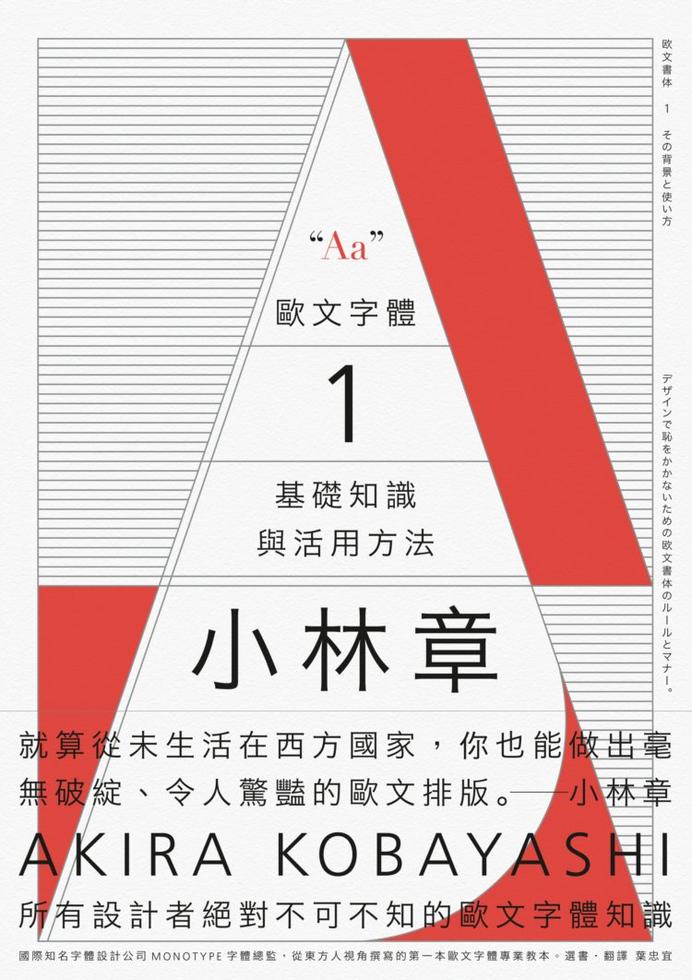
歐文字體(1)──基礎知識與活用方法
小林章
「就算從未生活在西方國家,也能做出毫無破綻、令人驚豔的歐文排版。」
歐文字體基礎知識X經典字體特色與選用方法X排版原則與規範
國際知名字體設計公司Monotype字體總監--小林章
從東方人視角撰寫的第一本西洋字體專業教本
所有設計者不可不知的字體知識
──從歷史起源、用語解說、經典字體解析等觀念知識,到字體設計、辨識、選用、業界規則等實戰技巧,讓你有系統地通盤理解歐文字體,徹底活用!
本書作者小林章,在獲得多項國際字體設計大獎後,受聘至字體大廠德國Linotype(現和Monotype字體公司合併)擔任字體設計總監,並與字型大師合作設計出多款膾炙人口的字型。
擁有豐富歐文字體設計經驗的他,將經驗有系統性的整合,透過本書以深入淺出的方式呈現給所有對字型、字體有興趣,想進一步了解相關知識的讀者。不論你只是對字體感到好奇,或者是設計相關科系學生、設計領域工作者,甚至未來也想成為一名字體設計師,本書將能讓你深度理解歐文字體的歷史背景與使用方式,從細節到整體全面掌握,大幅增進你的設計力及鑑賞力。
本書架構──
‧第一章:文字的形成
要真正學習字體設計,必須先從歐文字體的歷史源頭談起。為什麼歐文字體會發展成現在的樣貌?第一章透過簡單動手畫及清晰的圖解,帶讀者了解歐文字體的成因,打好觀念基礎。
‧第二章:理解歐文字體
第二章介紹了在理解歐文字體前須具備的必要知識。
第一節「用語解說」,介紹了與字體相關的基本用詞定義,例如「字體、字形、字型」的個別定義及使用時機;有襯線體、無襯線體、草書體、哥德體等基本字體種類的特徵及其歷史背景;「字體排印設計師(typographer)」和「字體設計師(type designer)」的不同之處;「襯線」、「基線」、「x字高」、「上伸部/下伸部」、「字間調整」等字體設計的專門用語定義;什麼是「字型家族」?一個字型家族又是由哪些不同「字重」的字體所組合而成的?
一套字型除了拉丁字母和數字以外,還有許多其他的構成要素,稱為「字符」。第二節「字型的內容」將告訴你各種西洋標點符號、空格、連字等拉丁字母和數字以外的這些字符名稱、輸入法以及使用方法。
第三節「值得信賴的經典字體」,列舉出了十數種古今中外最常使用的歐文字體,並加以分門別類,告訴你這些字體的歷史、特色及使用方式,讓你了解這些字體受歡迎背後的秘密,也讓你從此能夠將這些字體運用自如。
第四節「沒有壞字體,卻有壞字型」,舉出數個壞字型的例子與好字型進行比較,並解說各自的優劣之處,教你該如何看出一個字型的好壞。
第五節「各種Garamond和Caslon」,將各家廠商的Garamond」及Caslon系列字體做比較,我們能發現即使是以同一組活字為基底,各家廠商做出來的字體還是有許多不同之處。
第六節「避免出糗的排版規範」告訴我們在歐文字體的排版上,有一些最基本、不該犯的錯誤,避免因為字體的排版讓整個作品的專業度大減。
‧第三章:歐文字體的選用
歐文字體的種類繁多,此章將告訴讀者在針對不同的設計品、設計目的時,該如何從時代、國情、氛圍上考量,挑選出最適合的歐文字體。
‧第四章:享受歐文字體樂趣的方法
以第二章〈避免出糗的排版規範〉為基礎,本章將介紹更進階的排版規範和應用方法。例如:字母的大小寫如何搭配、分別該在什麼狀況下使用;各種數字的使用方法;草書體的運用該如何掌握;「文字間距」該如何微調;該如何活用各種形式的字體為設計加分……
‧第五章:從歐文字體設計師的角度
作者於本章由字體設計師的角度出發,以他曾製作過的字型為案例分享經驗,並分享他做為一個字體設計總監,在看待字體設計時所思考的事。並親自介紹了他所設計過的數種字體,你能看見一個字體背後的故事及成因。
‧第六章:想跟未來新進們分享的事
小林章身為東方人,何以能在歐文字體界裡獲得如此高的成就?在最後一章,他將和讀者分享在字體設計這條路上一路走來的心路歷程,以過來人的角度給予後進許多實用的建議與心得,給想成為字體設計師或相關領域的人相當難得的指引。